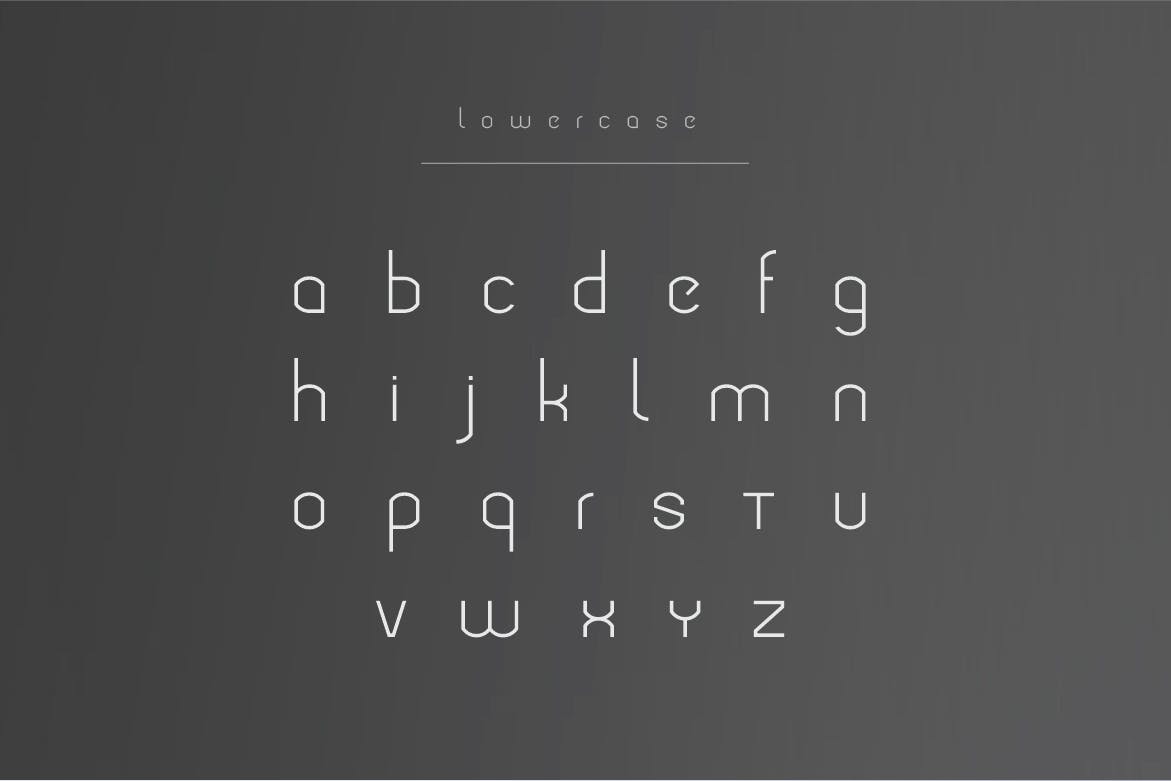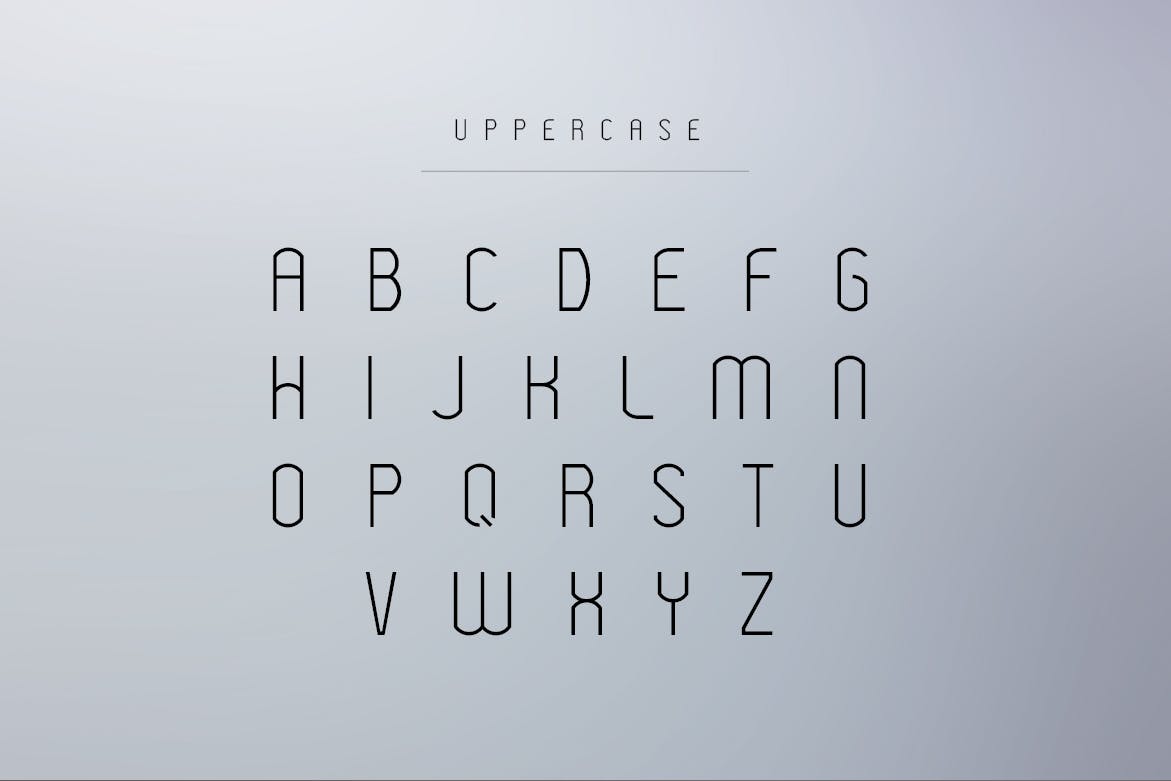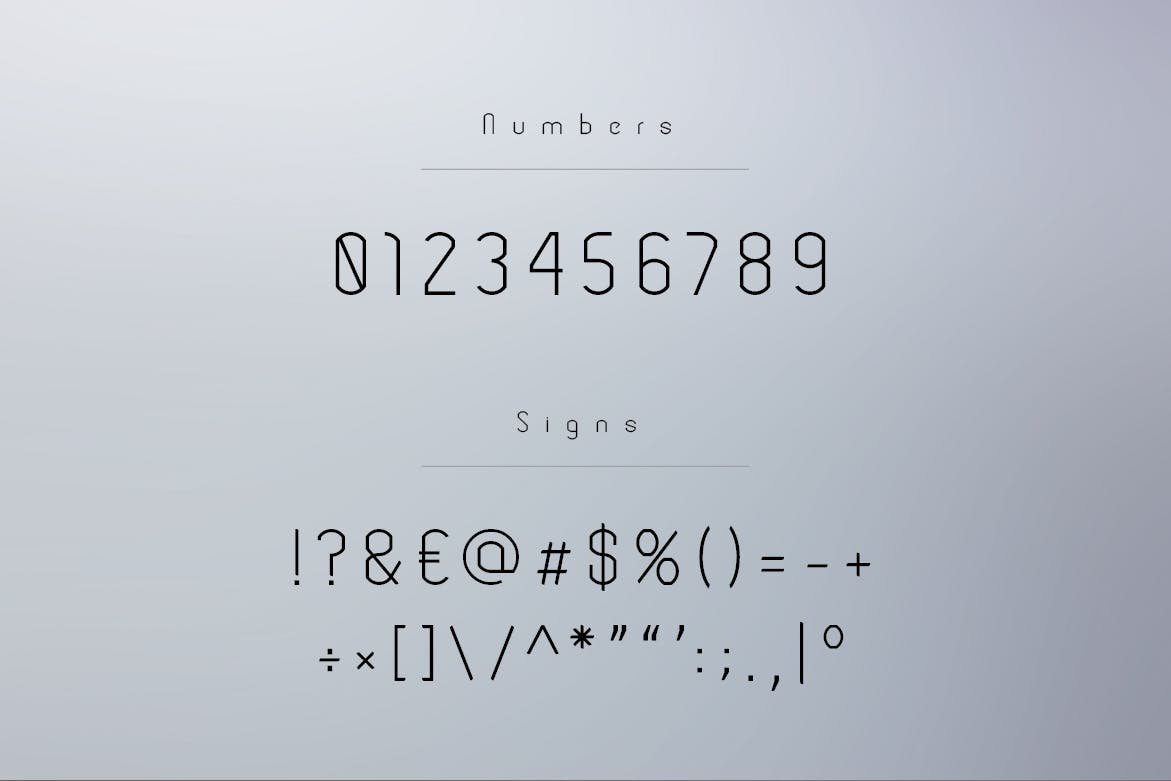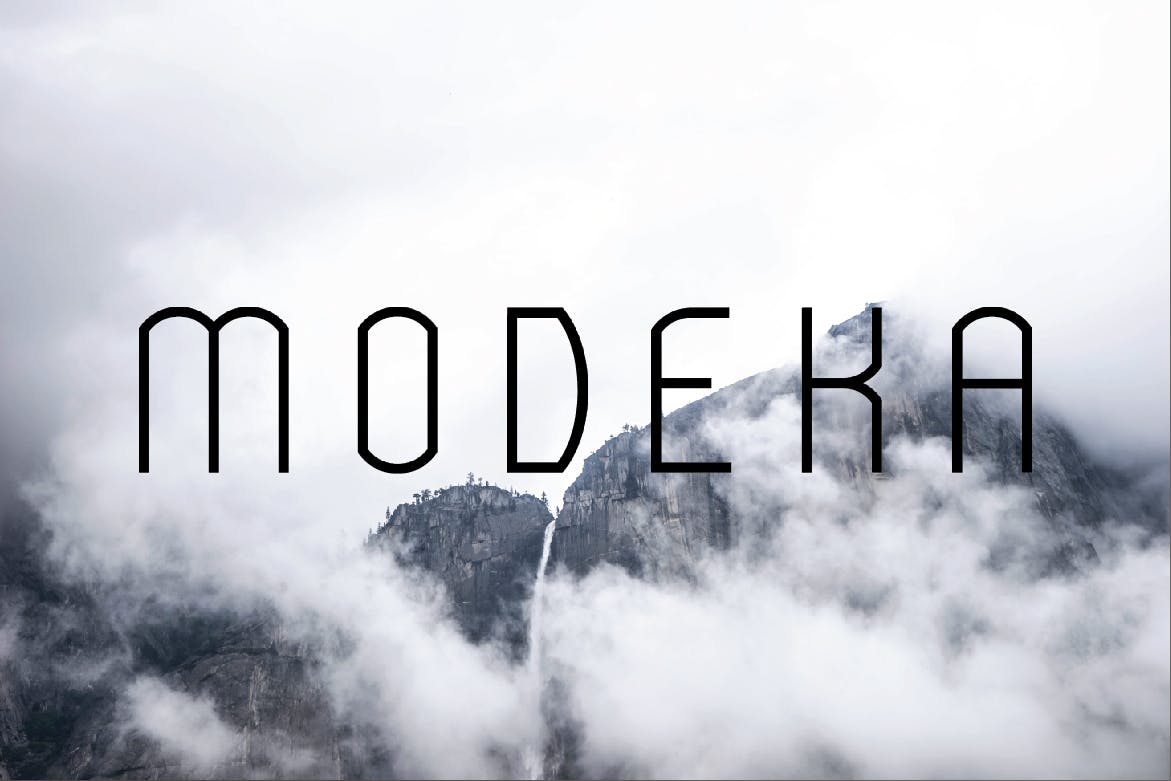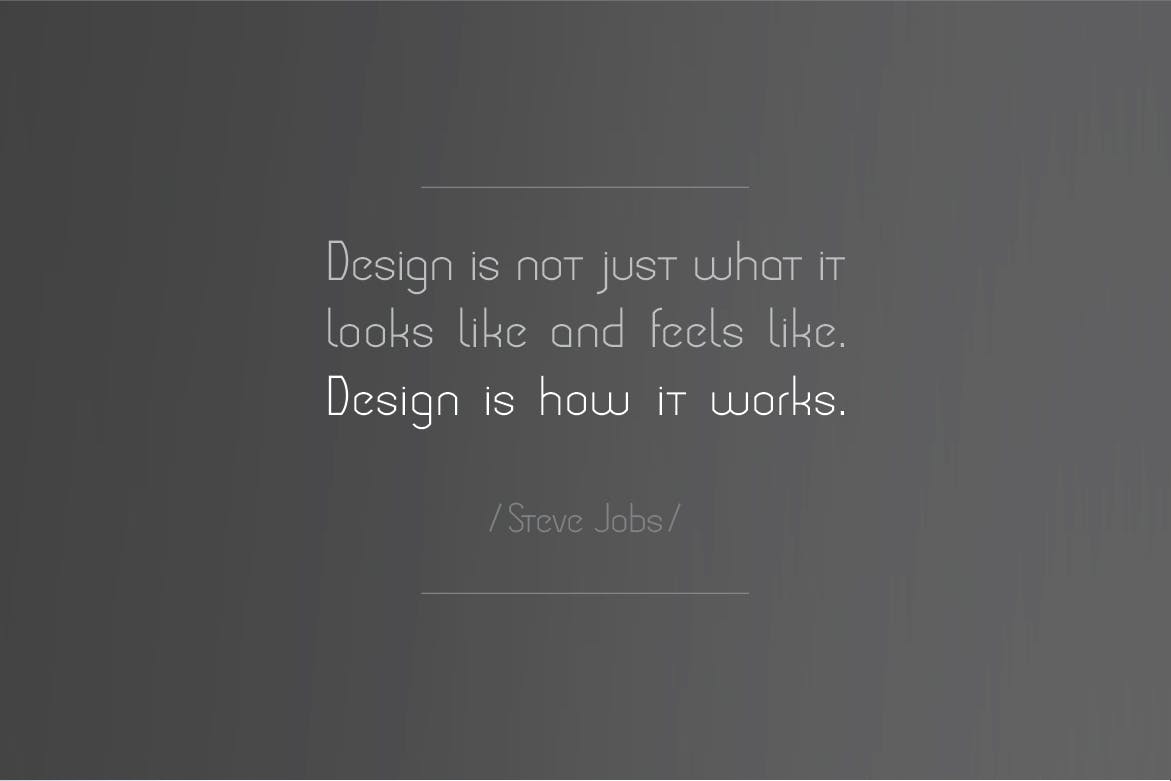
دانلود فونت مدرن Modeka با طراحی شیک و جذاب
Modeka Modern Font
فونت مدرن Modeka با طراحی زیبا برای پروژههای شما.
فونت Modeka یک فونت مدرن و بدون سر با طراحی منظم و شیک است که جذابیت خاصی به پروژههای شما میبخشد!
مناسب برای طراحی وب و گرافیک
قابل استفاده در پروژههای تبلیغاتی
خوانایی بالا و طراحی زیبا